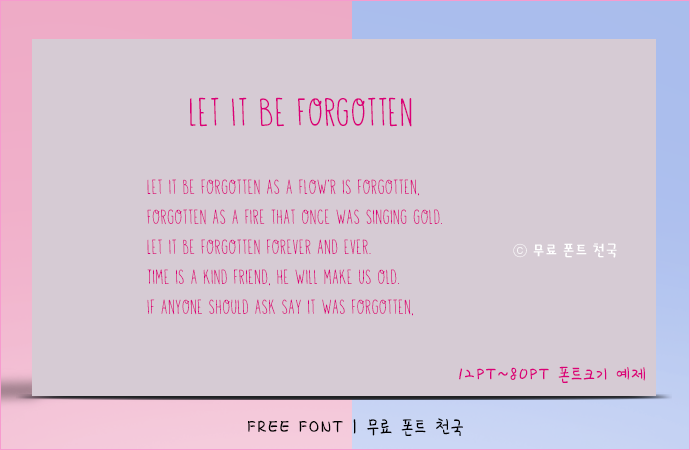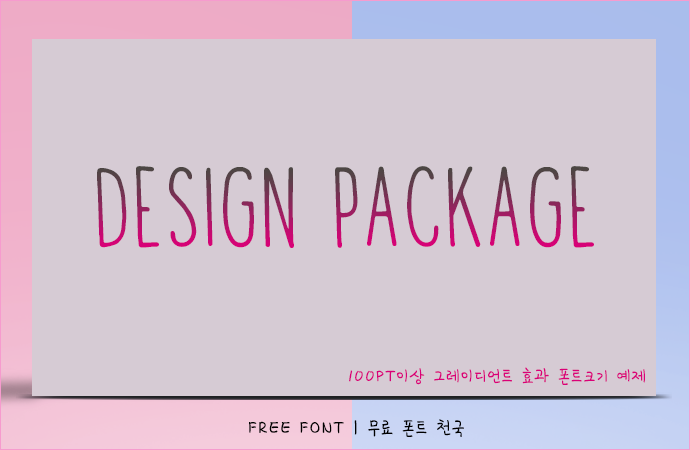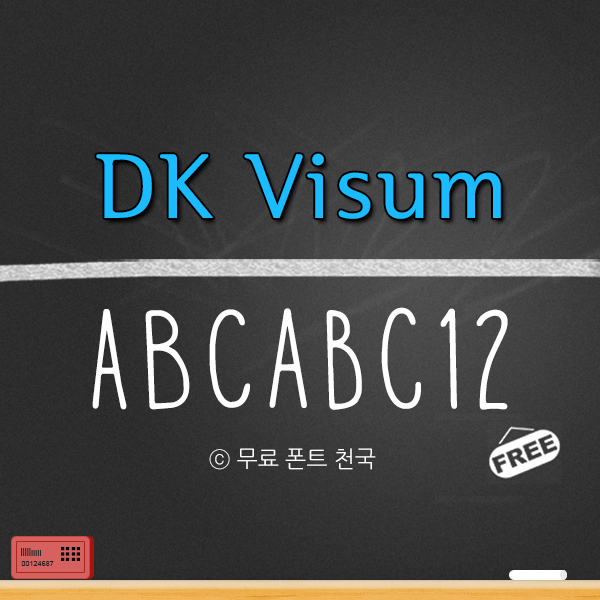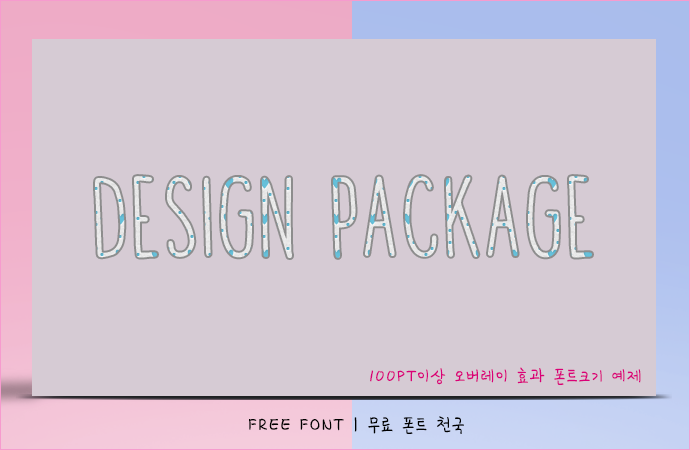
기다란 스타일의 DK Visum 영문폰트
서체 자체가 긴 스타일로 제작된 깔끔하고 담백한 스타일의 DK Visum 영문 폰트입니다. 작은 폰트보다는 큰 제목이나 간단한 문장에 매우 잘 어우릴 것 같은 폰트입니다. DK Visum 폰트는 누구나 무료로 자유롭게 사용 가능한 폰트입니다.
DK Visum 폰트 # 미리보기
DK Visum 폰트, 12~80PT 크기로 적용한 효과
DK Visum 폰트, 100PT 크기 이상으로 작업한 오버레이 효과
DK Visum 폰트, 100PT 크기 이상으로 작업한 그레이언트 효과